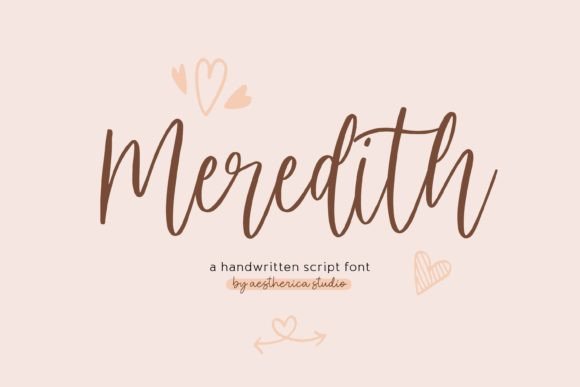
Meredith
適切なデザイン要素を見つけるのは難しい場合がありますが、Meredithは作品を即座に引き立てる優れたコレクションを提供します。
精密に作られたMeredithは、クリーンなベクター、滑らかなタイポグラフィ、そして安心のための商用ライセンスを提供します。
POD(オンデマンド印刷)製品、結婚式の招待状、またはソーシャルメディアのグラフィックを作成している場合でも、Meredithは理想的です。